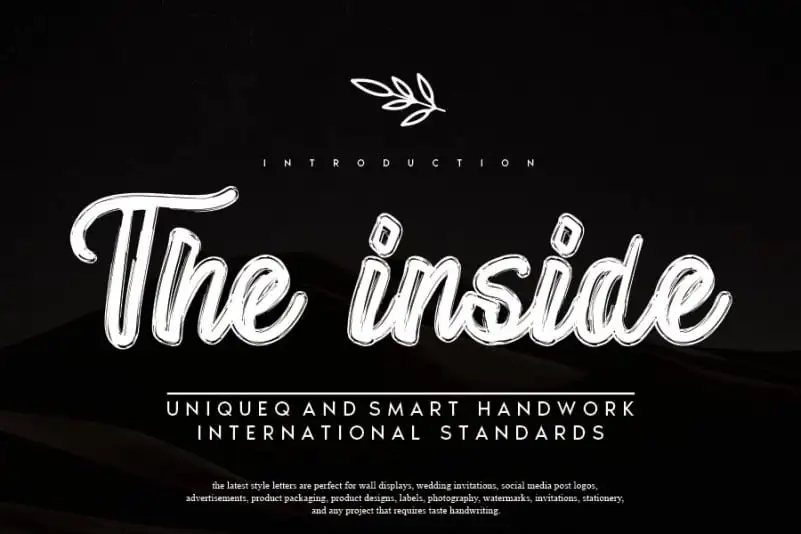
The inside Script Font – Download Grátis
A The inside Script Font é uma elegante tipografia feita à mão que mantém seus influentes traços de calligrafia enquanto transmuda para algo contemporâneo e moderno. Inspirada por escritas artesanais, esta tipografia se destaca como um ícone em sua categoria, fornecendo uma sensação de sofisticação com uma pitada de frescura que nunca é forçada. Descubra seu próprio encanto com The inside Script Font, uma escolha perfeita para projetos que buscam o melhor no estilo e na qualidade. Transforme suas ideias em algo único com este fonte inigualável, ideal tanto para designers profissionais quanto para iniciantes apaixonados por gráficos.